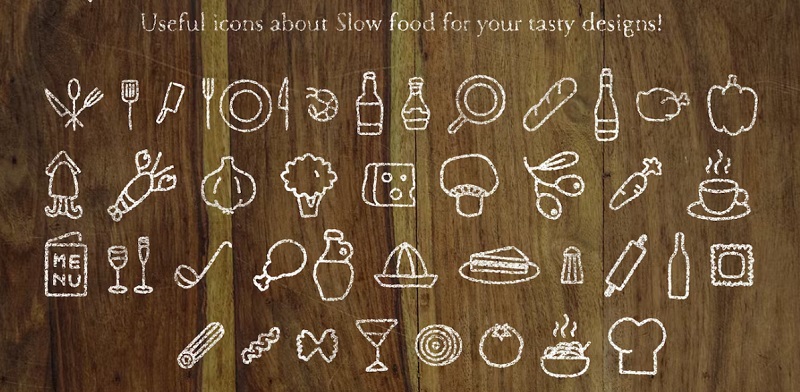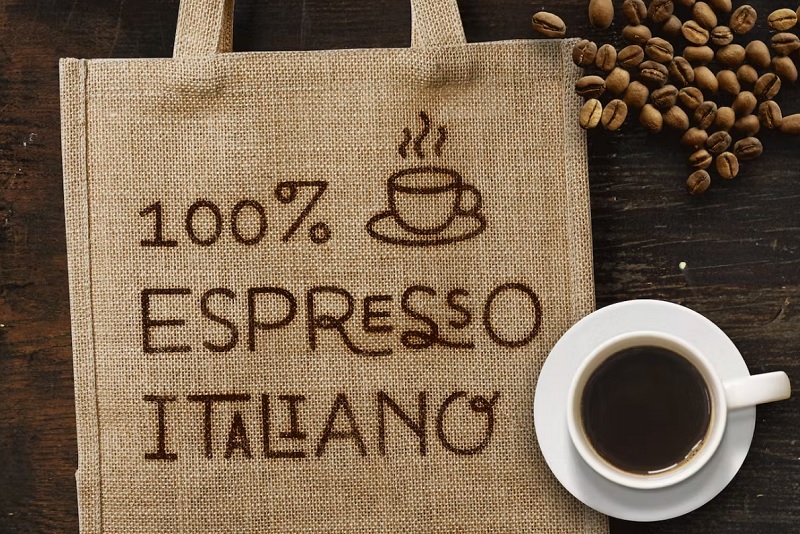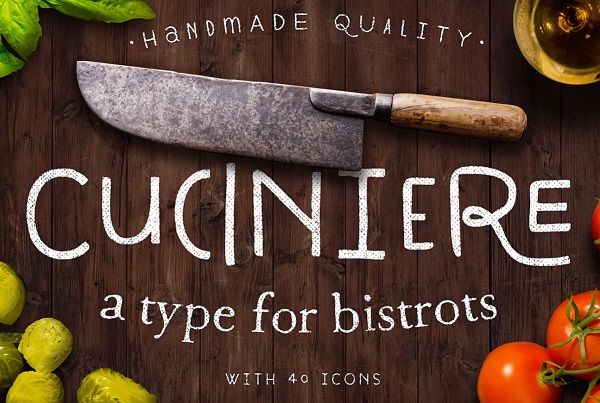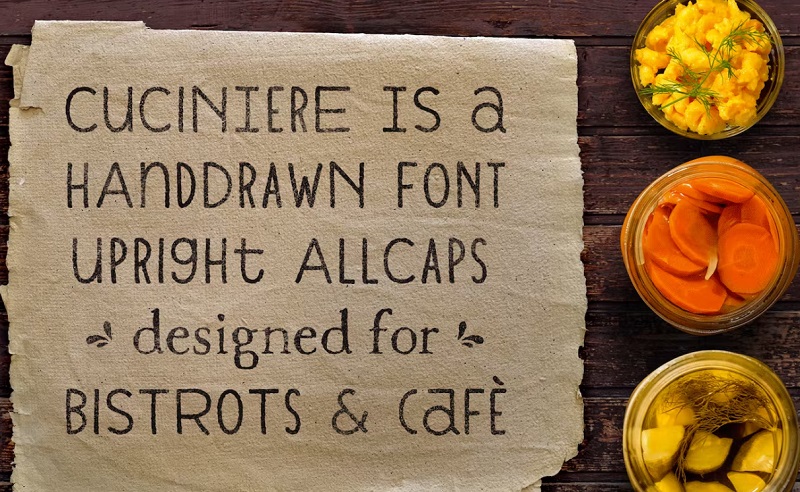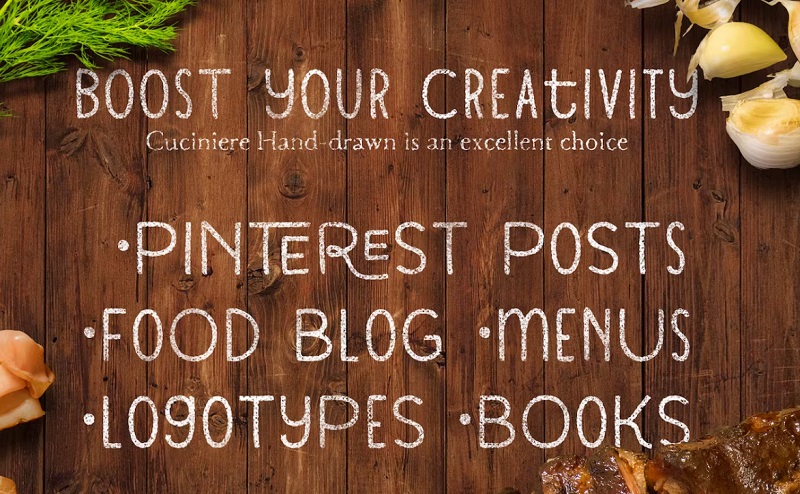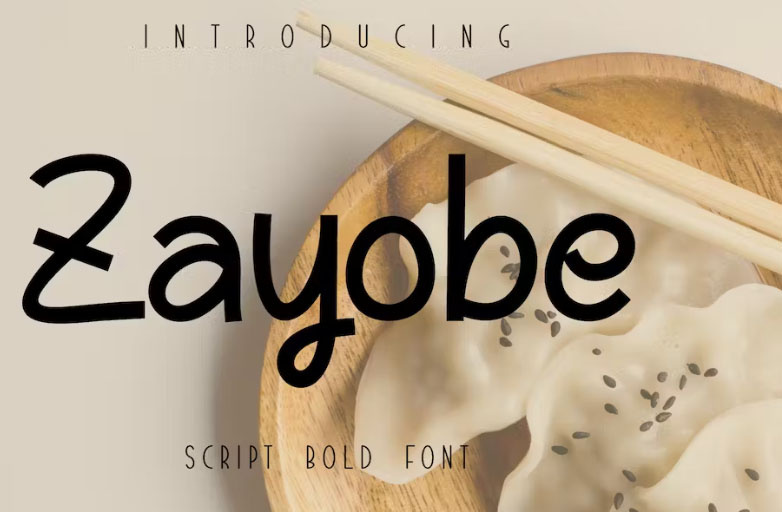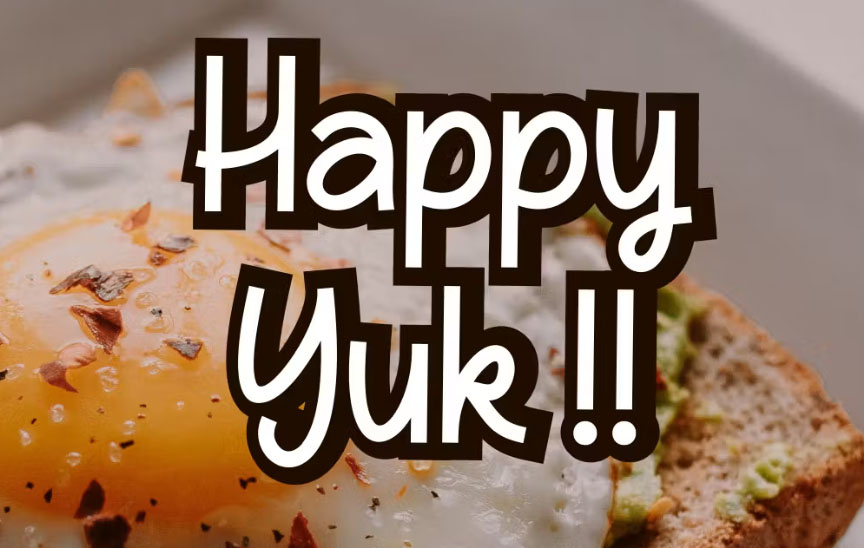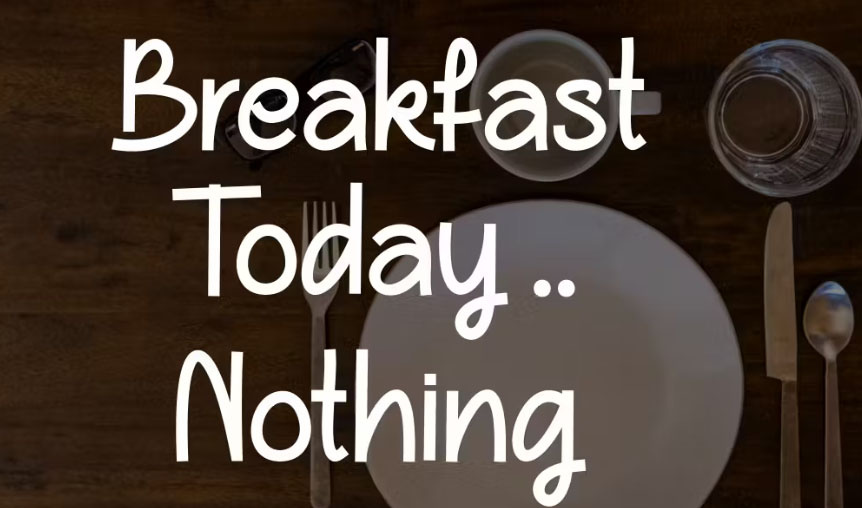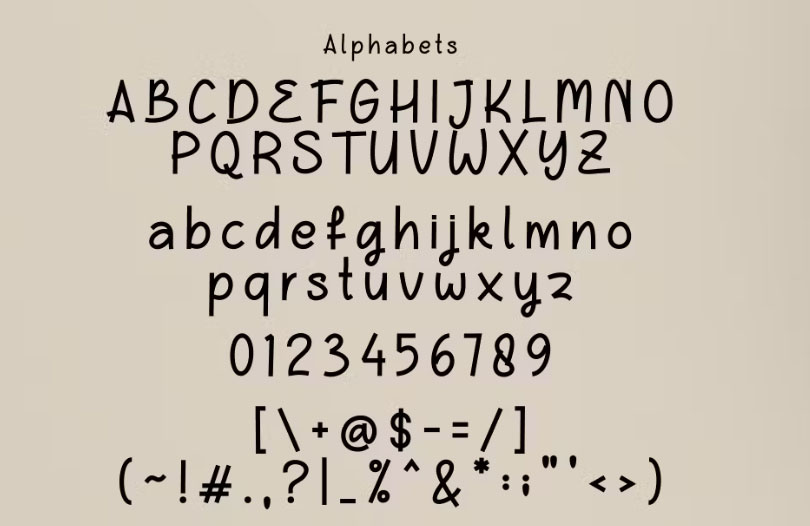
فونت انگلیسی زیبا با موضوع غذا و آشپزی آپدیت 2024
فونت انگلیسی زیبا و جدید با موضوع غذا و آشپزی
در این مطلب با دانلود فونت های انگلیسی زیبا و جدید Cuciniere font با موضوع غذا و آشپزی در جی اف ایکس دانلود همراه شما هستیم.اگر برای طراحی منو،کاتالوگ یا بروشورهای تبلیغاتی کافه ، رستوران ، فست فود یا سایر موضوعات دیگر مرتبط با غذا به دنبال فونت مناسب هستید این مطلب مناسب شماست ! توسط فونت انگلیسی Cuciniere font می توانید طراحی های فوق العاده زیبایی را انجام دهید و مخاطبانتان را تحت تاثیر قرار دهید . در ادامه می توانید پیش نمایش های مختلف این فونت غذا را تماشا کنید و فایل اصلی را از سایت دانلود نمایید.
فونت انگلیسی غذا برای طراحی منو کافه،کافی شاپ
دانلود فونت انگلیسی با موضوع غذا و آشپزی
فونت انگلیسی غذا و آشپزی در جی اف ایکس دانلود
فونت انگلیسی غذا و آشپزی +40 آیکون رایگان
1- دانلود فونت انگلیسی با موضوع غذا در جی اف ایکس دانلود
• نام فونت انگلیسی Cuciniere font
به همراه 40 آیکون از پیش آماده
فونت انگلیسی فست فود Zayobe
2- فونت انگلیسی غذا و نوشیدنی Zayobe
فونت انگلیسی مناسب برای غذا، نوشیدنی یا هر چیز مرتبط با آن. فونت انگلیسی غذا و نوشیدنی Zayobe قابل استفاده برای طراحی انواع منو، کاتالوگ غذا، بنر های وب سایت و غیره می باشد. فقط با فرمت .otf و .ttf موجود است.
فونت انگلیسی غذا و آشپزی
3- دانلود فونت انگلیسی غذا و آشپزی
این فونت غذا با نام Milkya Food می‌تواند حس و حال غذا را منتقل کنند، اشتها را تحریک کنند و به برند شما هویت ببخشند. مناسب برای طراحی‌های مرتبط با غذا و آشپزی، منوهای رستوران‌، بسته‌بندی محصولات غذایی و ... می باشد.